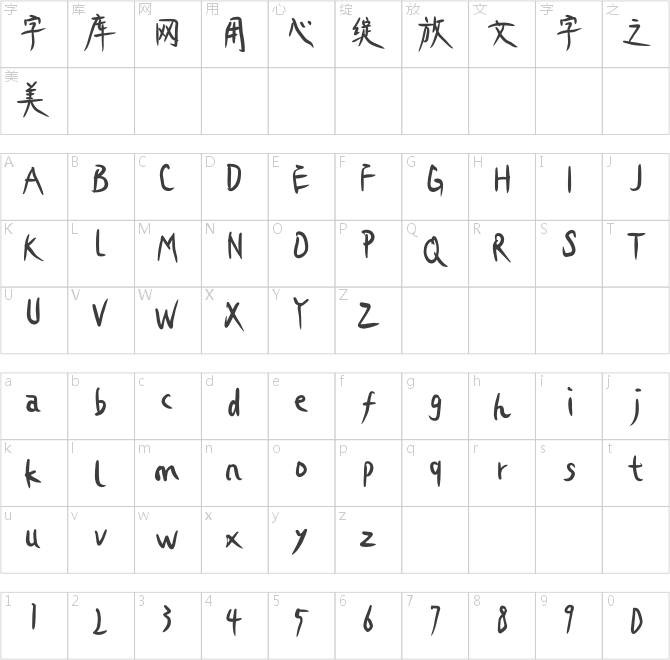
字體名稱: 造字工房失樂體
造字工房失樂體
造字工房失樂體介紹
造字工房失樂體,字形舒展靈動。筆畫粗中帶細、錯落有致、收放有度。整體風格緊中見放,簡淡秀潤。字體中大量弧線的應用,令其更顯婉轉流暢,給人以酣暢瀟灑之感,有極強的視覺表現力。適用于大標題及個性品牌設計推廣等環境。本字體為簡體字庫,采用OpenType/CID格式,Adobe-GB1-5編碼,基于中華人民共和國GB2312-80字符集標準。